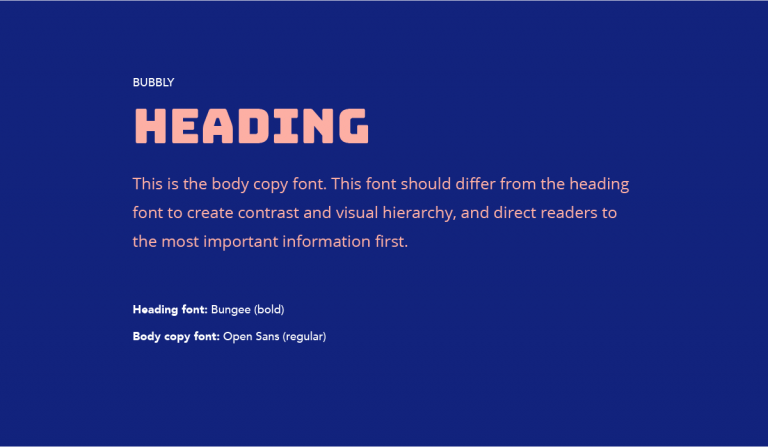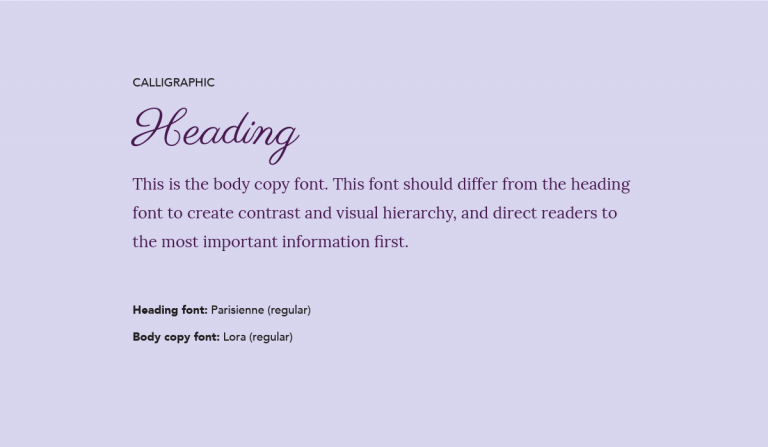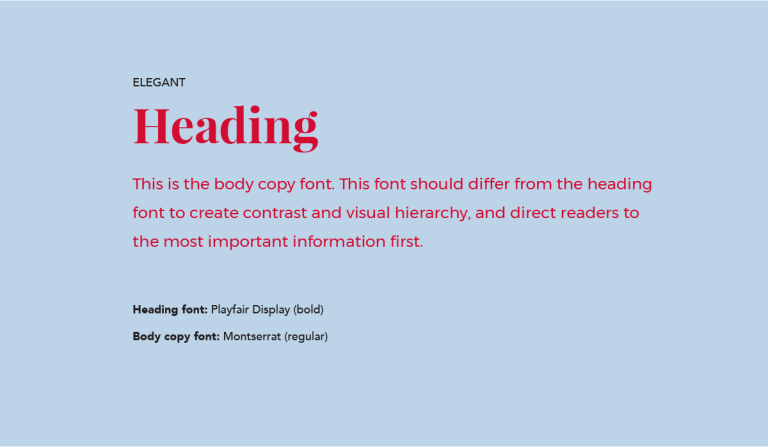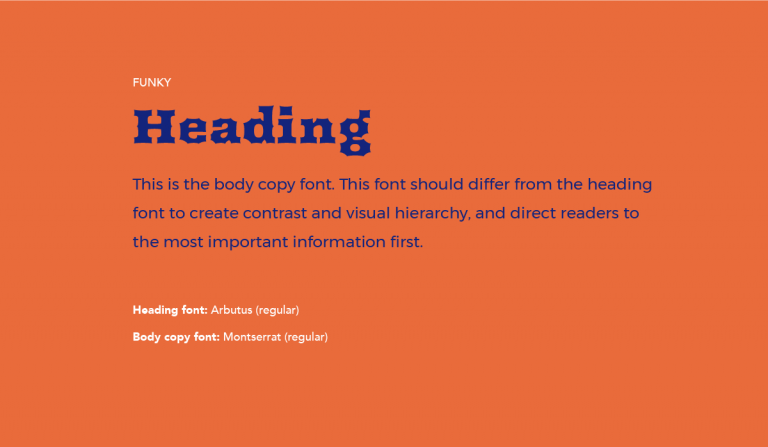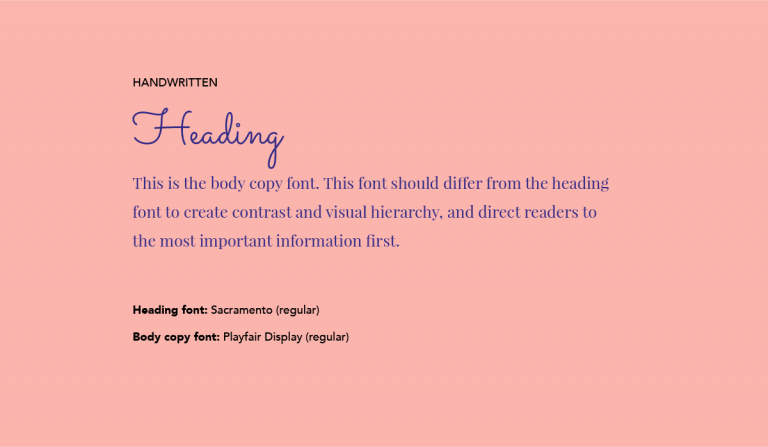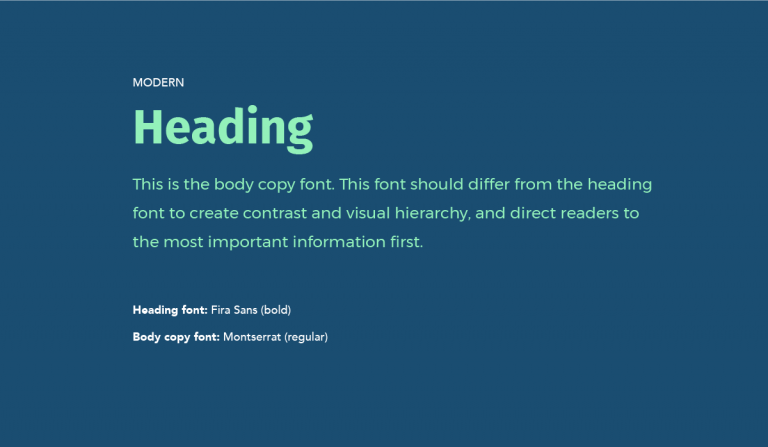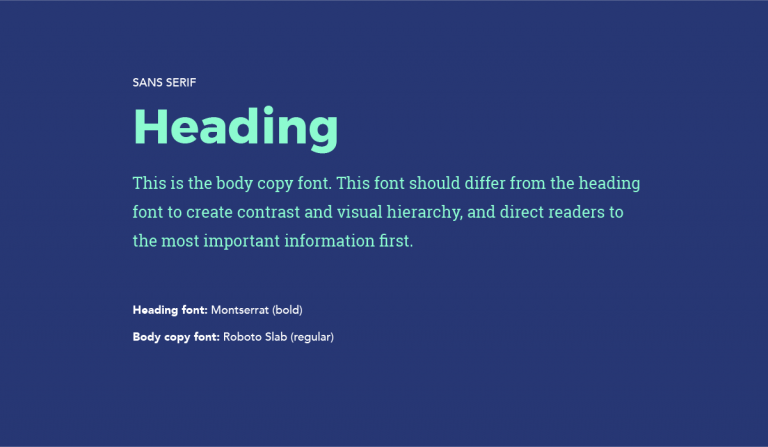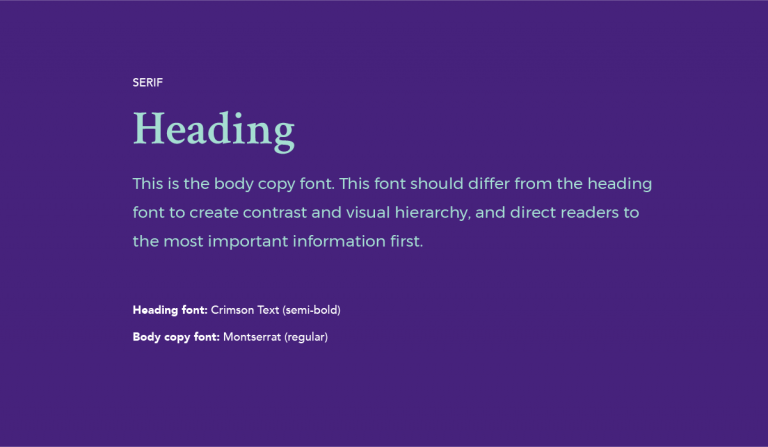
11 cặp font chữ đẹp cho thiết kế logo
Font chữ đẹp trong thiết kế logo luôn là điều đầu tiên kết nối với khách hàng trước khi họ bắt đầu đọc các thông điệp được bạn truyền tải qua website hay lật giở cuốn brochure giới thiệu về thương hiệu của bạn. Mỗi font chữ đều đem lại một cảm xúc, tính cách và ấn tượng thị giác riêng. Các font chữ thậm chí còn trở nên mạnh mẽ hơn khi được dùng đối lập hoặc bổ sung cho nhau, đặc biệt là khi cung cấp sự tương phản. Vậy làm thế nào để chọn font chữ đẹp khi thiết kế logo của bạn? Làm thế nào để tìm được font chữ có thể kết nối với bản chất thương hiệu của bạn?
Chọn một font chữ cũng tương tự như đi sắm bộ quần áo mới. Bạn có thể mặc thử mọi thứ trong cửa hàng, nhưng bạn phải chọn thứ phù hợp nhất với phong cách riêng của bạn. Bạn nên chọn font chữ có thể thể hiện trực quan thương hiệu và các giá trị của bạn.
Ví dụ, nếu bạn là công ty dịch vụ tài chính, chọn một font chữ trang trí sẽ không phù hợp vì loại chữ này thường mang lại cảm giác nghệ thuật và sáng tạo thay vì tính bảo đảm và sự uy tin. Công ty công nghệ nên tránh font chữ viết tay vì font chữ này khó đọc trên khi được hiển thị trên các trang web và có thể không phù hợp với văn hoá hoặc sứ mệnh của công ty.
Cặp font chữ đẹp trong thiết kế logo là gì?
Cặp font chữ là bộ hai font chữ bổ sung cho nhau, giúp bạn có thêm lựa chọn khi thiết kế các ấn phẩm logo. Việc ghép cặp này sẽ cho bạn có font chữ để sử dụng trong heading copy (trên trang web, danh thiếp, ấn phẩm quảng cáo, thư mời, áp phích, v.v.) và body copy, chiếm phần lớn nội dung bạn viết.
Có thể bạn đang tự hỏi, chẳng lẽ tôi không thể sử dụng các font chữ trên logo làm font “chính” được ư? Đôi khi, câu trả lời là có. Nhưng cũng có những lúc, font chữ được dùng trong logo chỉ có một kích cỡ, do bạn tự thiết kế hoặc không phù hợp để làm heading copy hoặc body copy.
Hoặc có thể, logo của bạn là biểu tượng monogram, không bao gồm font chữ cụ thể.
Bằng cách lựa chọn một cách có chiến lược cặp font chữ kết hợp hiệu quả với nhau, bạn sẽ thu hút được sự chú ý của khách hàng, tạo ra một ấn phẩm dễ đọc, cân bằng, có khả năng thị giác (visual hierarchy) và tính tương phản cao hơn trong quá trình xây dựng logo.
Font chữ đẹp ảnh hưởng đến định hướng thị giác (visual hierarchy) trong thiết kế logo như thế nào?
Định hướng thị giác là quá trình sắp xếp nội dung để truyền đạt thông tin - hướng người xem đến thông tin quan trọng nhất trước, sau đó đưa họ qua phần còn lại của nội dung bằng các tín hiệu thị giác. Định hướng thị giác được truyền tải qua font chữ, màu sắc, hình ảnh, kích thước, và nhiều hơn nữa.
Khi bạn sử dụng cặp font chữ mà trong đó có một font chữ nổi bật hơn font chữ còn lại, người dùng sẽ biết đâu là nơi cần đọc trước tiên khi nhìn thấy font chữ heading. Đó là thông tin bạn muốn người dùng đọc được trước khi họ tìm hiểu phần còn lại của nội dung, để họ có được cái nhìn tổng quan về tất cả.
Font chữ heading và body là gì?
Heading luôn sử dụng phiên bản in đậm của các font chữ thông thường. Ví dụ, nếu bạn đặt font Avenir làm heading, bạn nên sử dụng bản in đậm hoặc nét to, không nên sử dụng phiên bản hẹp hoặc nét nhỏ.
Mặt khác, khi chọn font chữ body, bạn có thể dùng phiên bản thường. Như vậy, bạn sẽ không “hét” vào mặt người đọc hoặc khiến họ hoang mang không hiểu đâu mới là nội dung chính.
Hai font chữ đẹp cho thiết kế logo có cần thiết không? Tôi sẽ áp dụng chúng vào đâu?
Không, không phải lúc nào bạn cũng cần đến hai font chữ. Bạn có thể sử dụng các phiên bản khác nhau của một font chính. Lại lấy Avernir làm ví dụ, bạn có thể dùng phiên bản in đậm để làm tiêu đề và bản thường để làm nội dung
Khi bạn đã chọn được một font chữ hoặc cặp chữ, bạn có thể áp dụng chúng vào hầu hết mọi ấn phẩm của thương hiệu, bao gồm trang web, posters, banners, brochures, menus, hình ảnh trên các trang mạnh xã hội, bài đăng trên blog, trang phục công ty, đồ dùng văn phòng.
Chúng tôi sẽ giúp công đoạn chọn font chữ trở nên đơn giản hơn bằng cách giới thiệu 11 cặp font chữ làm ví dụ, đại diện cho các kiểu phong cách khác nhau (sans-serif, serif, chữ cổ, chữ viết tay và hơn thế nữa). Ngoài ra, chúng tôi còn đặt các ví dụ này trong ứng dụng thực tế để bạn có thể tham khảo thêm!
Cặp chữ #1: Tiêu đề dùng font Sans-Serif + Nội dung dùng Slab
Font chữ không chân luôn rất dễ đọc. Chúng vô cùng hiệu quả khi được sử dụng trong các ấn phẩm in lớn với chất lượng cao cũng như khi hiển thị ở độ phân giải thấp hơn, điều này đã khiến font chữ không chân trở nên hoàn hảo để dùng trên trang web hoặc ebooks.
Trong ví dụ trên, chúng tôi đã chọn font chữ Montserrat in đậm làm heading — một font chữ không chân đẹp mắt và gọn gàng — kết hợp cùng font Roboto Slab in thường, làm hình ảnh thêm phần thú vị mà vẫn rõ ràng và dễ đọc.
Bạn có thể thấy rõ ràng hiệu quả của cặp font chữ này trên danh thiếp, khi tên đóng vai trò quan trọng nhất, đi kèm với các thông tin liên lạc.
Cặp chữ #2: Tiêu đề dùng font serif + Nội dung dùng font sans-serif